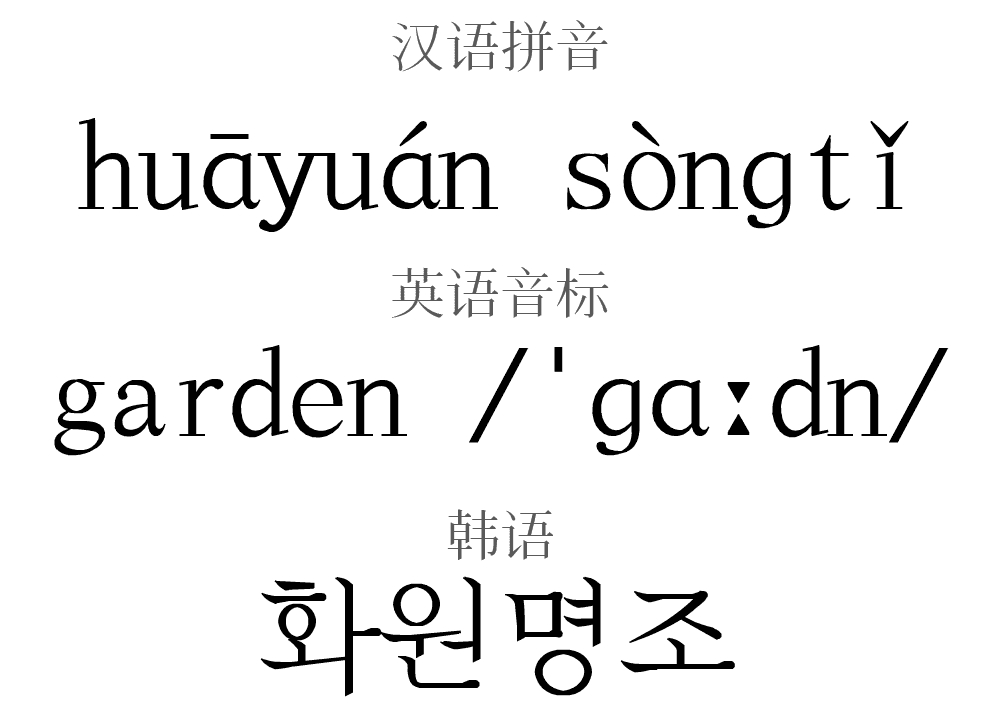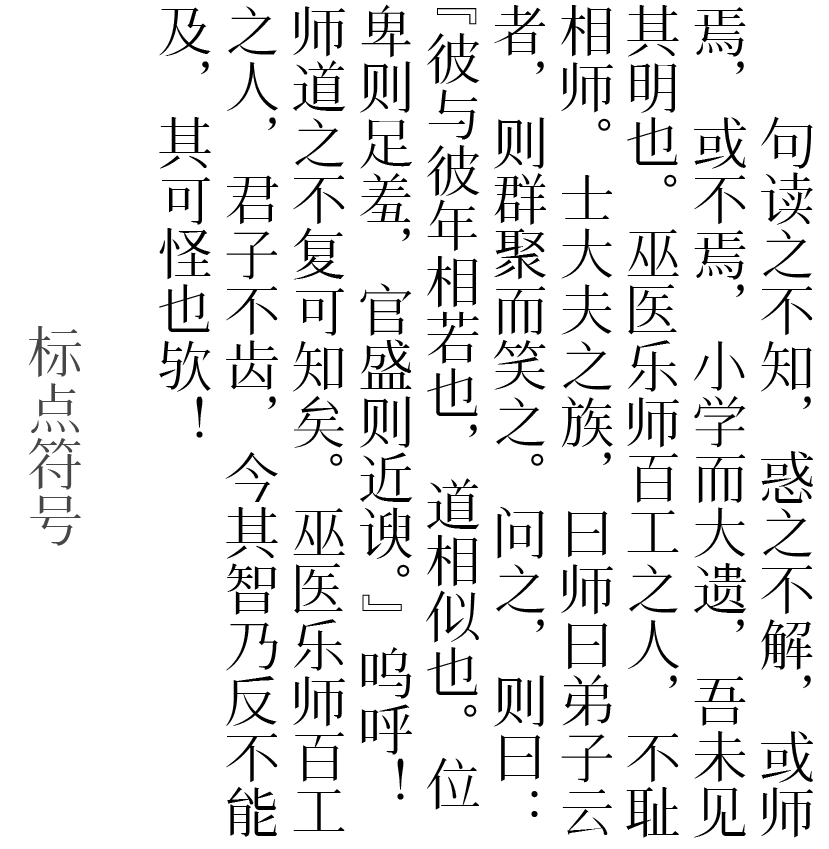
花園明朝 (Hanazono) 是一款免費字體,根據字形維基(GlyphWiki)所開發,幾乎收錄了所有漢字字形。缺點是字形以日本字形為準,有一些字不符合中文書寫規範(不論是大陸規範還是港臺規範)。在我瞭解到了字形wiki這個網站後,我決定將花園明朝體改成適合我們大陸人實用的版本。
起初,我只是單純地將字形維基中的國標字形搬運過來,結構方面沒有作改動,後來收到了大家的批評意見,才開始對這套字體用心製作。後來,經過多版的改造,《花園宋體》日漸地成熟。
《花園宋體》最初定的英文名是“HYSong”,後來發現與漢儀字庫的英文名“HY×××”撞車,所以我決定將字體名稱做改動。我保留了“花園”的“花”字,另起名為《飛花宋體》,英文名也改為“FlyFlowerSong”。
《飛花宋體》收錄GB2312-80的6763個漢字、《通用規範漢字表》的8105個漢字、《現代漢語通用字表》的7000個漢字。此外按需增加一些較常用的表外漢字,包括古文裡的字,同樣只有簡體。
其中,部分漢字的大陸字形並未製作,我也使用kage editor(HTML5)進行了創作。
符號方面,目前將HKSCS、GB2312、Big5所收錄的符號全部收錄並作了修整,此外有選擇地收錄了日標和韓標的一些符號。
飛花宋體是根據花園明朝體改編的一款字體,不僅收錄了大陸簡體的 6763 個漢字,還支持俄語、希臘語、韓語、拉丁語、盲文以及中學階段涉及的數學符號。